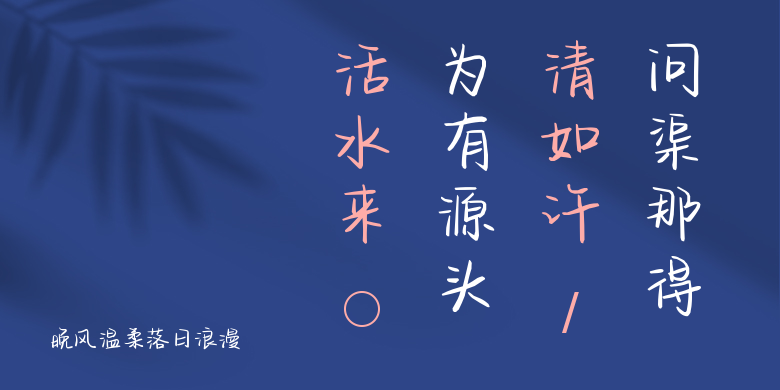
晚风温柔落日浪漫
晚风温柔落日浪漫,这款字体结构工整、笔画清晰,兼顾美观与易读性,适用于标题、正文、海报、包装、LOGO 等多种场景。字形优雅稳定,风格百搭耐看,适配日常排版与创意设计,让文字呈现更舒适、更具质感。晚风温柔落日浪漫一笔一画,皆是细节,以均衡的比例、流畅的线条打造舒适视觉体验,字形端正大气,风格简约现代。无论是商业设计、品牌宣传还是日常排版,都能轻松驾驭,让文字更有格调与力量。晚风温柔落日浪漫字体下载。